Bringt ein Kurs auf Papier mehr als ein digitaler Kurs fürs iPad, wenn beide am Ende dieselbe Handschrift trainieren sollen? Diese Frage begleitet mich bei jedem neuen Eintrag in meinem Handlettering-Vergleich. Fünf Anbieter stehen in diesem Produkttest nebeneinander, von klassischen Brushlettering-Kursen über Sketchnotes bis zu kostenlosen YouTube-Tutorials, und der Kursvergleich zeigt vor allem eines: Online-Lernen ersetzt keine Struktur, es verlangt danach.
Meine Antwort fällt differenziert aus. Wer noch nie einen Brush Pen in der Hand hatte, lernt auf Papier schneller, wo der Druck sitzen muss, weil das Material sofort Rückmeldung gibt. Wer schon ein iPad besitzt und ohnehin digital weiterarbeiten will, kann diesen Zwischenschritt auslassen, dann zahlt sich der direkte Einstieg in den digitalen Kurs eher aus. Der Rest dieses Vergleichs erklärt, woran das liegt.
Wer fängt besser mit Handlettering auf Papier an?
Der klassische Weg beginnt mit Fineliner oder Brush Pen auf Papier, und genau hier zeigt sich, wie viel Übung bis zum ersten sichtbaren Unterschied nötig ist. Wie lange das im Schnitt dauert, habe ich getrennt aufgeschlüsselt: Handlettering lernen Dauer geht genauer auf das Übungsvolumen ein, das für spürbaren Fortschritt nötig ist.
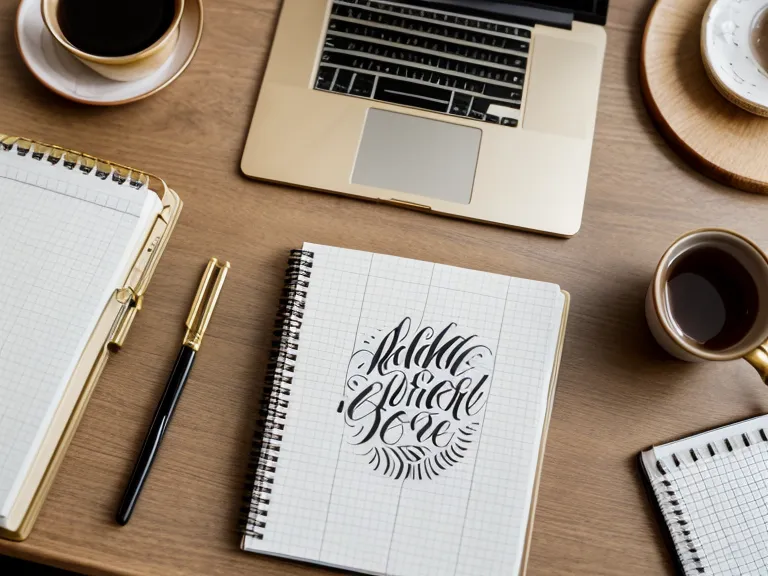
Die Druckkurve, also der Übergang vom hauchdünnen Aufstrich zum kräftigen Abstrich, ist das Detail, an dem sich Kurse am stärksten unterscheiden, wie man sie im Einzelnen aufbaut, ist aber ein eigenes Thema. Wie viel Gegendruck die Borsten im ersten Moment leisten, bevor sie überhaupt nachgeben, sagt mehr über die spätere Linienstärke aus als jede Anleitung im Kurs. Spannender im direkten Vergleich ist die Reihenfolge, in der geübt wird: Der analoge Handlettering Kurs von Timothy90 startet mit einzelnen Grundstrichen auf leerem Papier, bevor überhaupt ein Buchstabe auftaucht, und genau diese Geduld am Anfang war der Punkt, an dem ich am ehesten hätte aufgeben können.
Für den Einstieg ohne iPad ist der Handlettering Kurs deshalb meine erste Empfehlung: kein Wochenendprojekt, sondern eher ein Vorhaben für mehrere ruhige Abende, wenn man die Kernmodule ernsthaft durcharbeiten will. Begriffe wie Ober- und Unterlänge kläre ich hier bewusst nicht im Detail, das ist ein eigenes Glossar wert, aber die Strichführung wird spürbar ruhiger, je konsequenter man die Grundübungen wiederholt.
Bevor ich auf Spezialpapier umgestiegen bin, habe ich mit normalem Druckerpapier geübt, und der Stift hat gehakt und gezogen, statt sauber über die Fläche zu gleiten. Die raue Oberfläche zerrt an der Spitze, bis die feinen Haare ausfransen. Welches Papier zu welchem Stift wirklich passt, wäre ohnehin eine eigene Testreihe wert, hier reicht der Hinweis, dass die Kombination über Frust oder Fortschritt entscheidet. Wie schnell ein Brush Pen bei falscher Papierwahl regelrecht ausleiert, ist ebenfalls ein Thema für sich.
Der Digital Lettering Kurs verändert die Übungsroutine komplett
Wer stattdessen gleich aufs iPad wechselt, übt unter anderen Bedingungen. Der Widerstand des Papiers fehlt, dafür lässt sich jeder Fehler rückgängig machen. Der Digital Lettering Kurs baut deshalb weniger auf Wiederholung von Grundstrichen und mehr auf das Verständnis von Ebenen und Pinseleinstellungen in Procreate. Ob der Umstieg vom Papier aufs iPad überhaupt sinnvoll ist oder man besser analog bleibt, habe ich separat gegenübergestellt: Digital Lettering Kurs oder analoges Üben?
Besonders die Streamline-Funktion federt zittrige Kurven ab, verlangt aber ein Gefühl dafür, wie stark man sie einsetzt, damit die Linie noch nach Handschrift aussieht und nicht nach Vektorgrafik. Eine Nachbarin von mir zieht seit Jahren Gemüse im Hochbeet auf dem Balkon, und wenn ich ihr davon erzähle, vergleicht sie es sofort mit Rankhilfen: Die Technik stützt nur, was ohnehin in die richtige Richtung wachsen will, ersetzen kann sie die Handbewegung nicht.
Sketchnotes und YouTube: zwei Nebenwege im Vergleich
Sketchnotes verfolgen ein anderes Ziel als schöne Handschrift. Es geht um Tempo und Symbole, nicht um Ästhetik. Der Sketchnotes Kurs bringt Container, Pfeile und kleine Icons bei, die sich in Meetings oder beim Mitschreiben schneller einsetzen lassen als ausgearbeitete Buchstaben. Warum sich das besonders für Leute im Agenturalltag lohnt, habe ich hier vertieft: Sketchnotes Kurs für Grafikdesigner.
YouTube-Tutorials wirken zunächst wie die günstigste Option, und für einzelne Verzierungen sind sie das auch. Was fehlt, ist die Systematik. Man lernt, wie ein Wort hübsch aussieht, aber nicht, warum die Proportionen beim nächsten Wort plötzlich kippen. Einen ausführlicheren Vergleich dazu gibt es hier: Brush Lettering Kurs oder YouTube? Wer ganz ohne Brush Pen anfangen will, landet ohnehin schnell bei Faux Calligraphy, aber das ist noch mal ein eigenes Kapitel.
Warum die Plattform-Kurse bei mir durchfallen